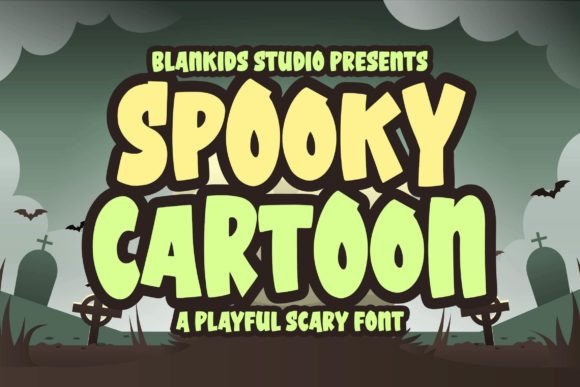
Spooky Cartoon
適切なデザイン要素を見つけるのは難しい場合がありますが、Spooky Cartoonは作品を即座に引き立てる優れたコレクションを提供します。
POD(オンデマンド印刷)製品、結婚式の招待状、またはソーシャルメディアのグラフィックを作成している場合でも、Spooky Cartoonは理想的です。